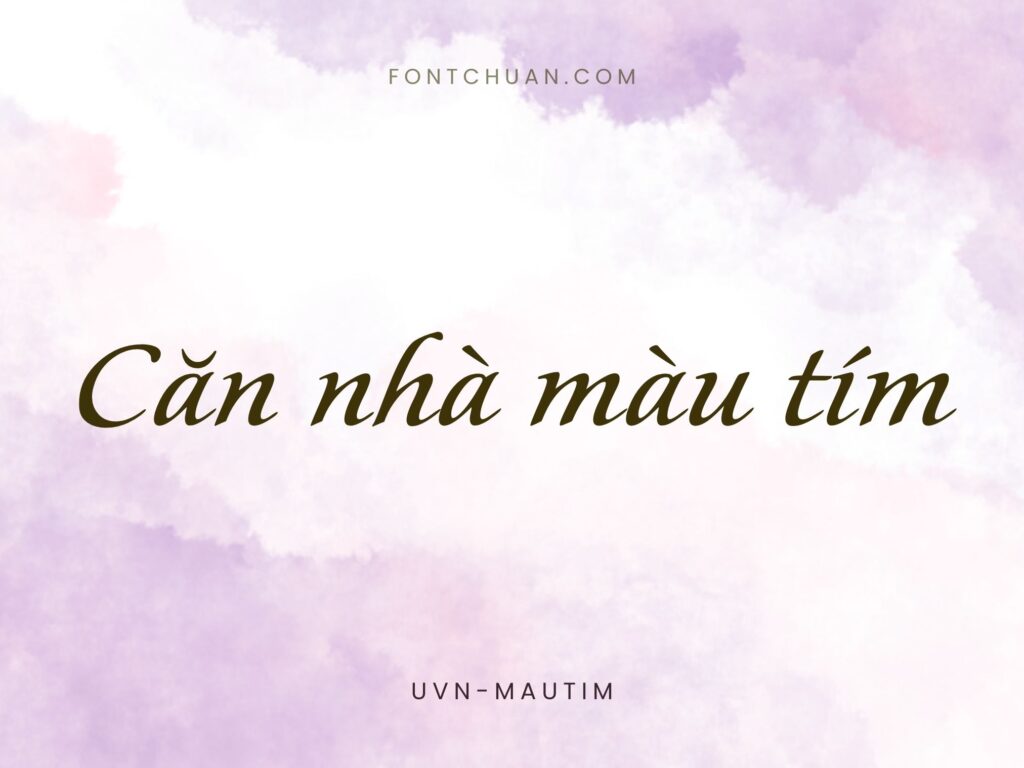
Font UVN Mau Tim Việt Hóa
UVN Màu Tím là một kiểu chữ script mang phong cách viết tay mềm mại và lôi cuốn, phản ánh sự tinh tế và sâu lắng của màu tím qua từng ký tự. Font này chỉ được sưu tầm và đăng bởi thành viên của Font Chuẩn.
UVN Màu Tím có thiết kế uyển chuyển, tạo cảm giác nhẹ nhàng và lãng mạn, phù hợp cho các ứng dụng như thiệp mời, bao bì sản phẩm, thương hiệu liên quan đến sức khỏe và sắc đẹp, cũng như các ấn phẩm nghệ thuật và thiết kế web. Các ngành nghề như quảng cáo, giáo dục, công nghệ và bất động sản có thể tận dụng UVN Màu Tím để tạo điểm nhấn độc đáo trong thiết kế.